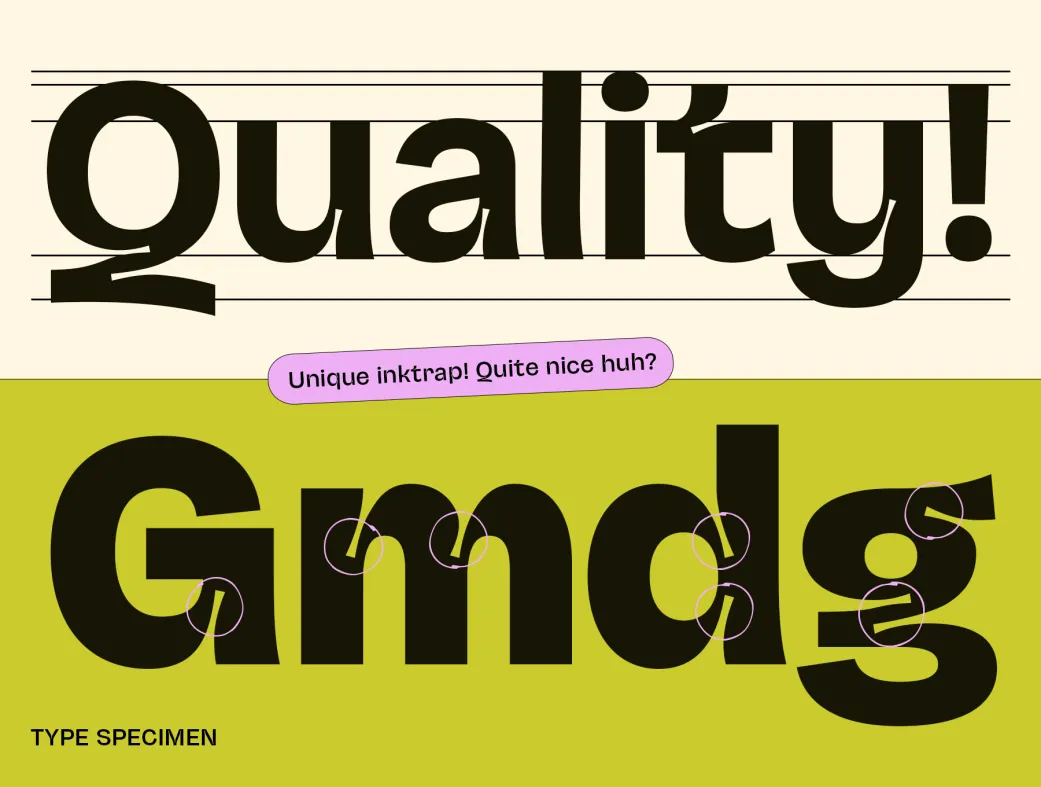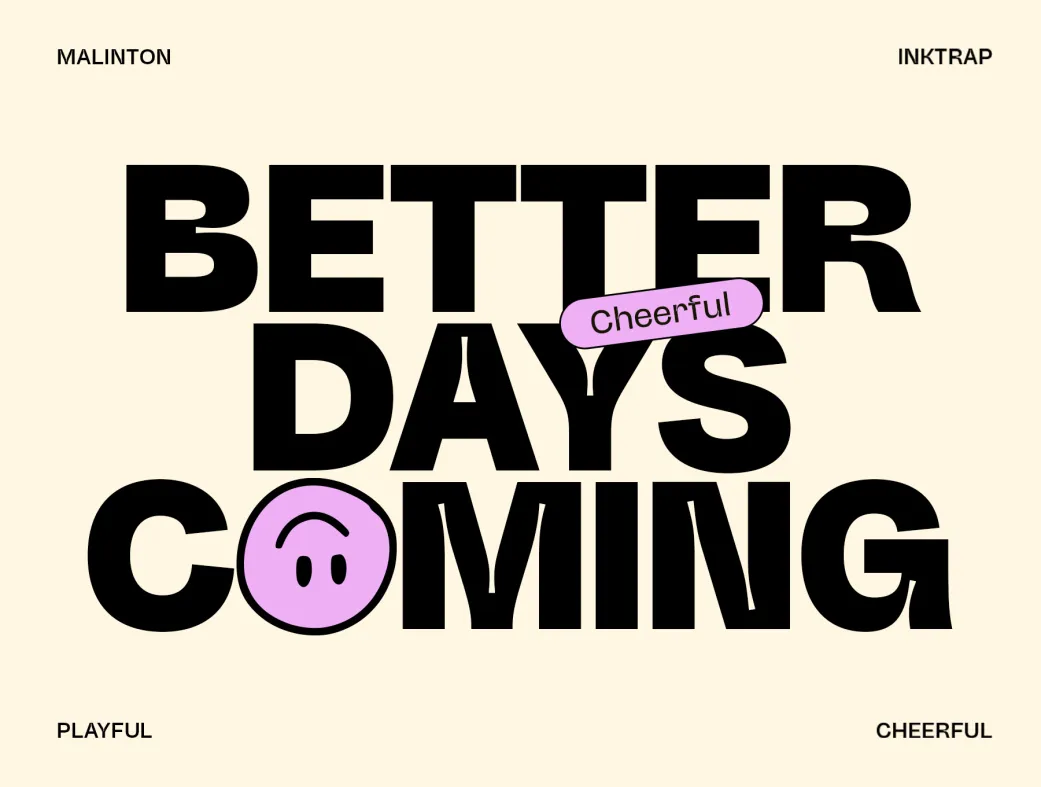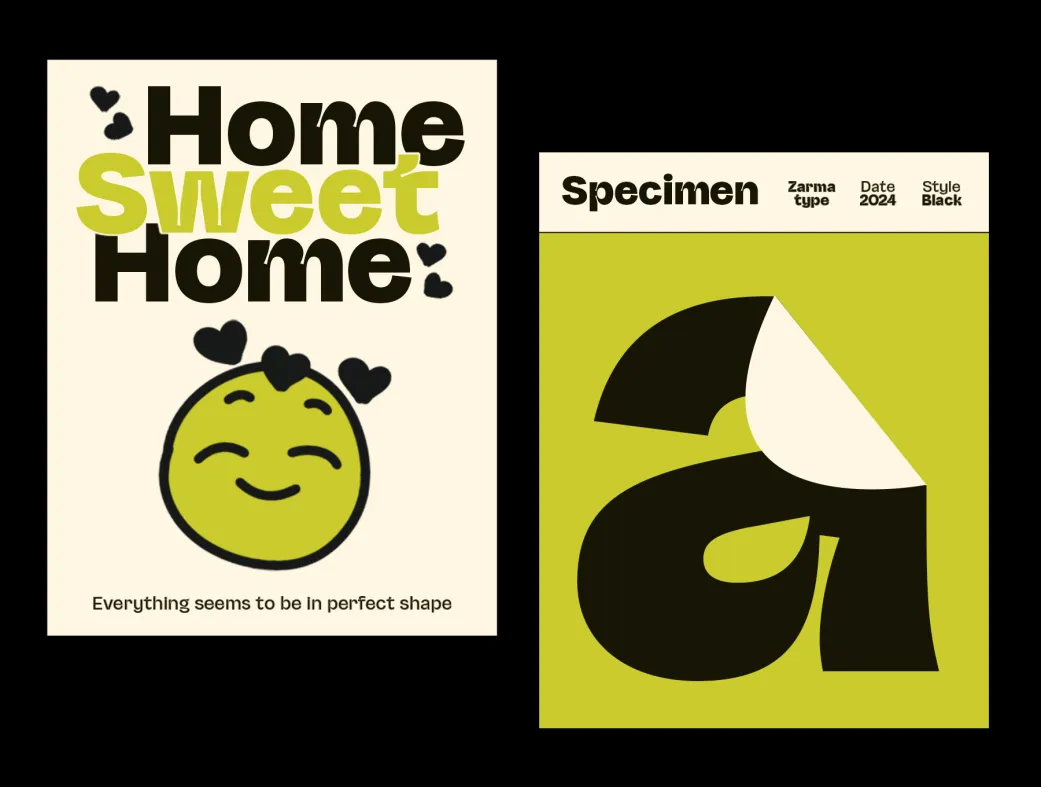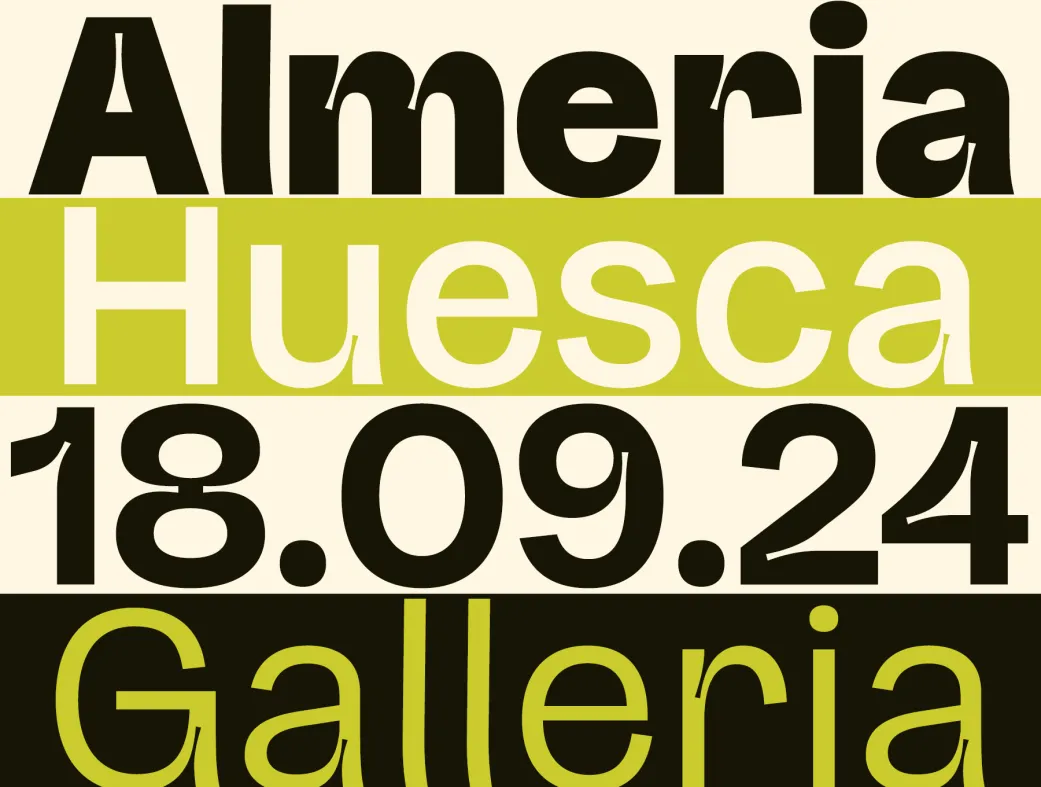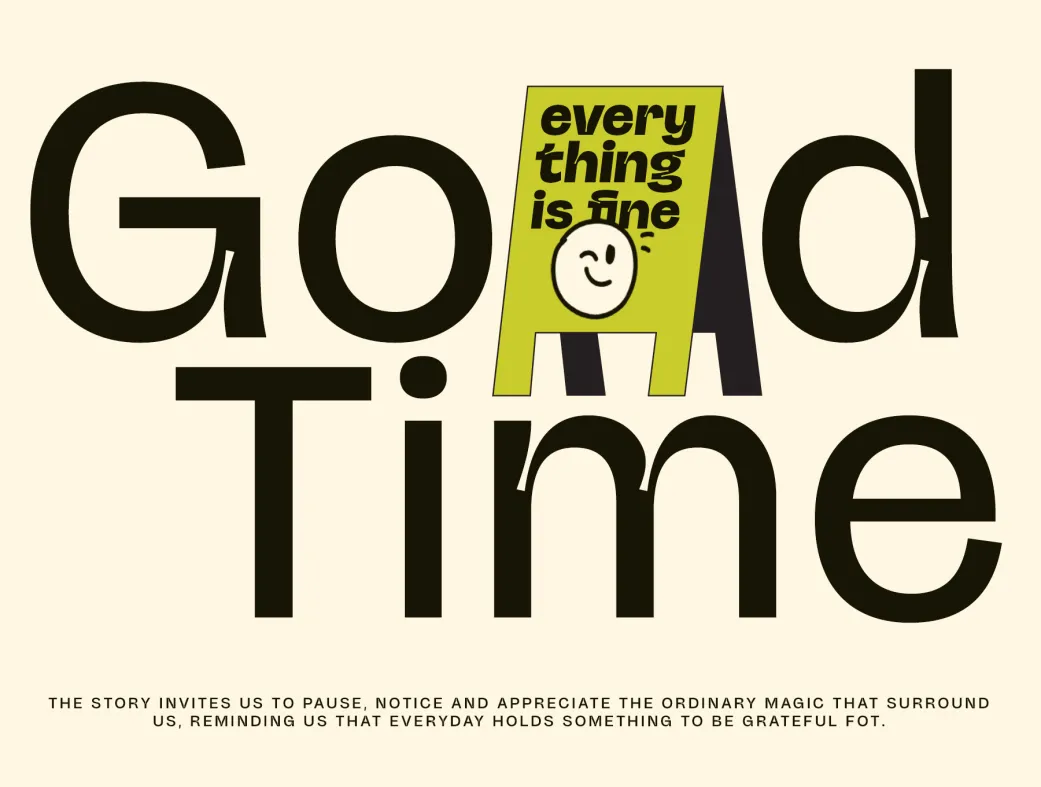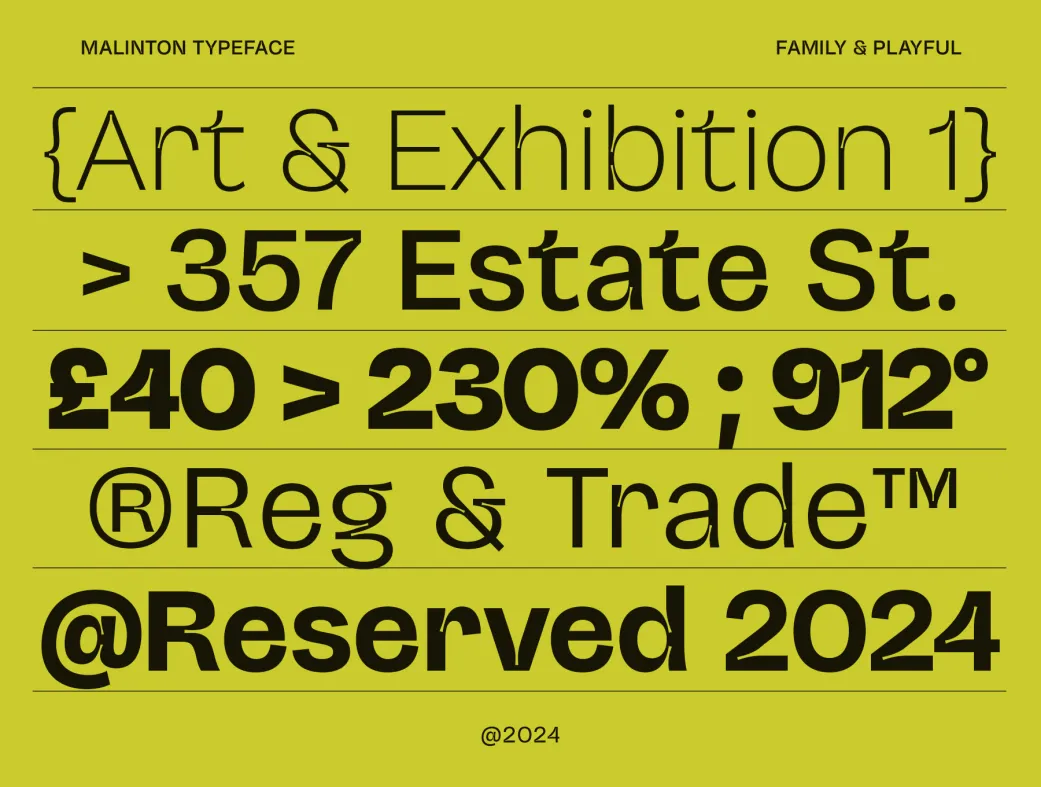
فونت سنس سریف مالینتون | Malinton
آیا به دنبال فونتی هستید که طراحی‌های شما را جذاب و حرفه‌ای کند؟ فونت مالینتون، با ۹ وزن متفاوت و طراحی منحصر به فرد، ایده‌آل شماست!
Malinton - Display Sans Serif Font
فونت سنس سریف مالینتون | Malinton | Malinton Display Sans Font Family
معرفی محصول:
فونت سنس سریف مالینتون، فراتر از یک فونت ساده است - این فونت به طراحی‌های شما شخصیت و جذابیت می‌بخشد! این فونت نمایش سنس سریف با ۹ وزن مختلف از Extra Light تا Black به دقت طراحی شده است و برای عنوان‌های شاد و بیانیه‌های جدی مناسب است.
ویژگی‌ها و مزایا:
این فونت با ویژگی‌های منحصر به فردی مانند درپوش‌های جوهری، جایگزین‌های شاداب ایموجی و پشتیبانی کامل از کاراکترها، ترکیب ایده‌آلی از ساختار حرفه‌ای و احساس دوستانه را به پروژه‌های خلاقانه شما اضافه می‌کند. چه در حال طراحی برای برندها، رسانه‌های اجتماعی یا محتوای ادیتوریال باشید، شخصیت متمایز مالینتون می‌تواند پیام شما را فراموش‌نشدنی کند.
فونت سنس سریف مالینتون با ویژگی‌های OpenType و فناوری فونت متغیر، گزینه‌ای ایده‌آل برای پروژه‌هایی است که نیاز به جلب توجه دارند در حالی که خوانایی و جذابیت حرفه‌ای را حفظ می‌کنند. با این فونت، شما می‌توانید به طراحی‌های خود عمق و تنوع ببخشید و هر نوع محتوای خلاقانه‌ای را به راحتی ارائه دهید.
کاربردها و نکات استفاده:
این فونت برای طراحان حرفه‌ای و مبتدی مناسب است. طراحان می‌توانند از آن در طراحی‌های برند، تبلیغات، و محتوای دیجیتال استفاده کنند، در حالی که مبتدیان می‌توانند به سادگی از این فونت برای متن‌ها و عنوان‌های خود بهره ببرند. توجه داشته باشید که با تغییر وزن‌ها، می‌توانید احساسات مختلف را به طراحی خود منتقل کنید.
3. آیا این فونت پشتیبانی از زبان‌های مختلف دارد؟
بله، فونت مالینتون با پشتیبانی کامل از کاراکترها، امکان استفاده در زبان‌های مختلف را فراهم می‌کند.
5. آیا این فونت امکان سفارشی‌سازی دارد؟
بله، فونت مالینتون دارای ویژگی‌های OpenType است که به شما امکان سفارشی‌سازی و تغییرات در طراحی را می‌دهد.